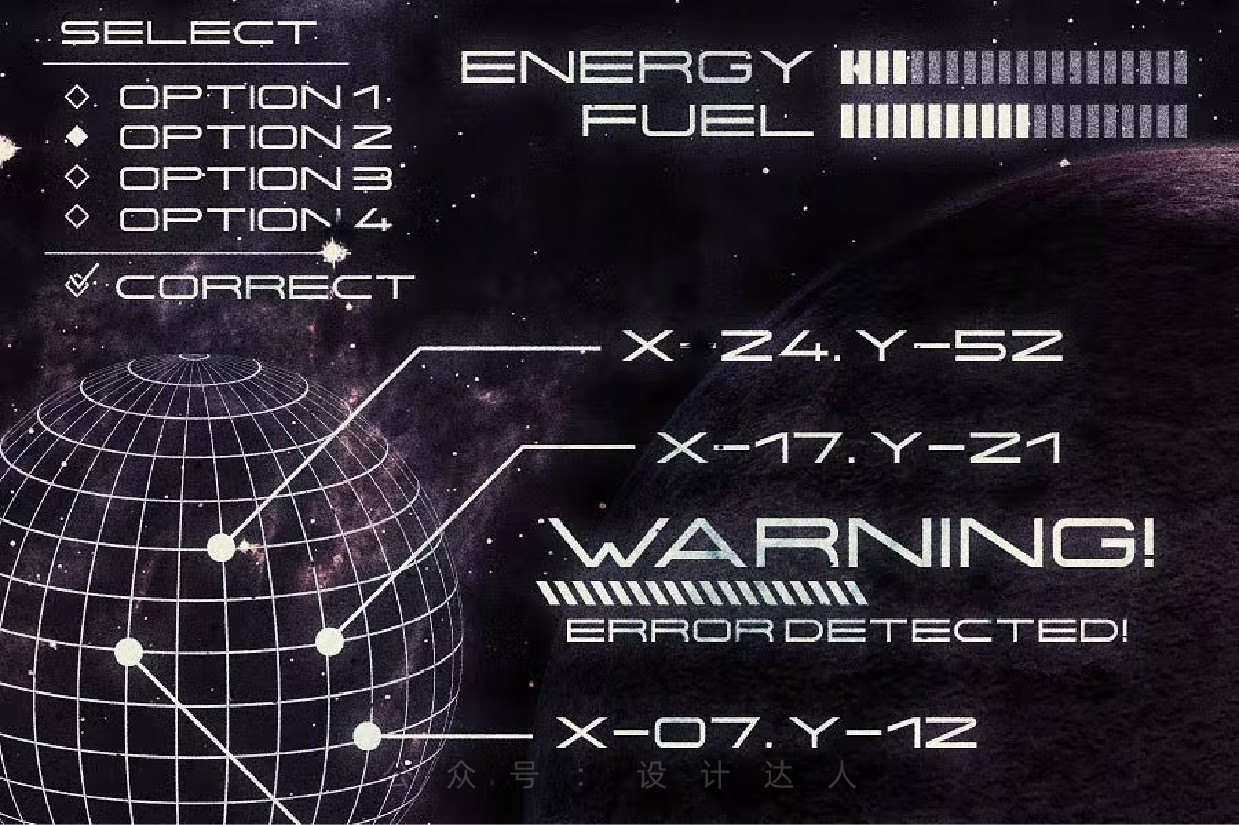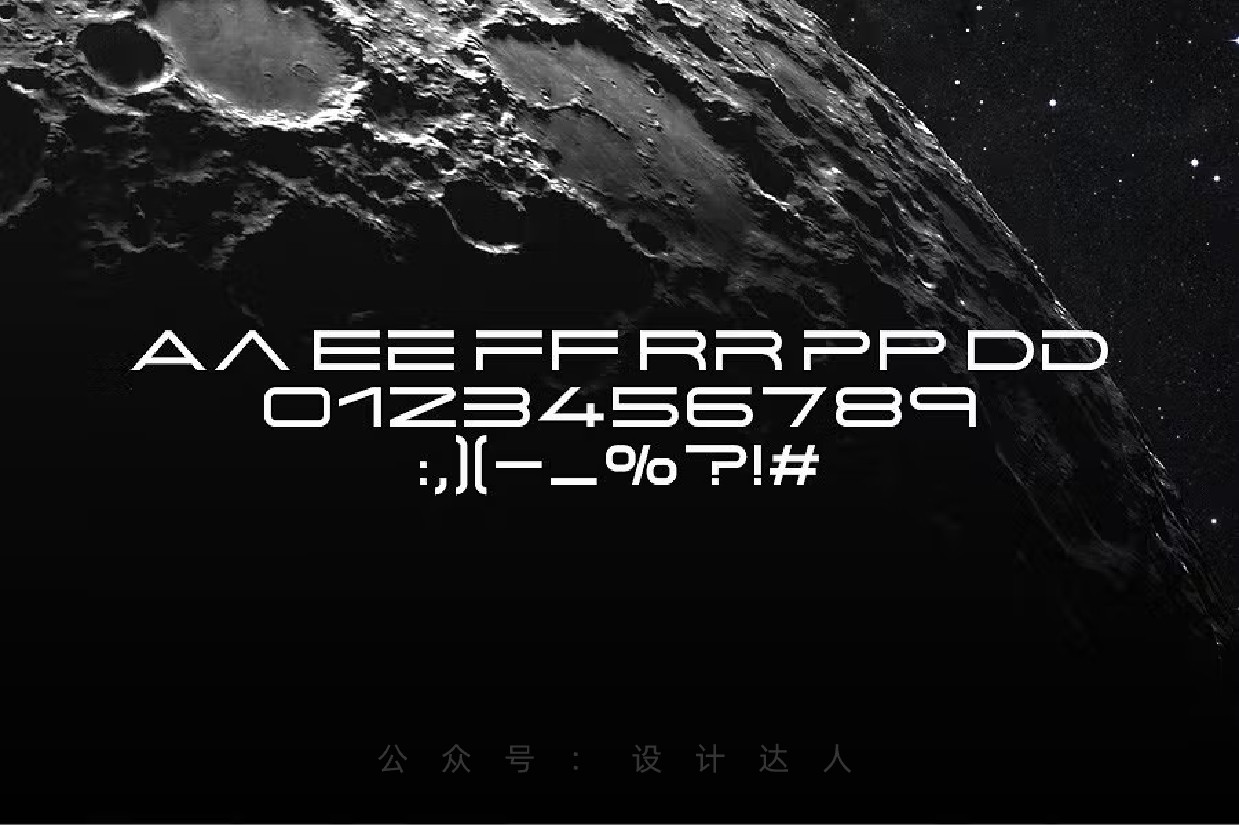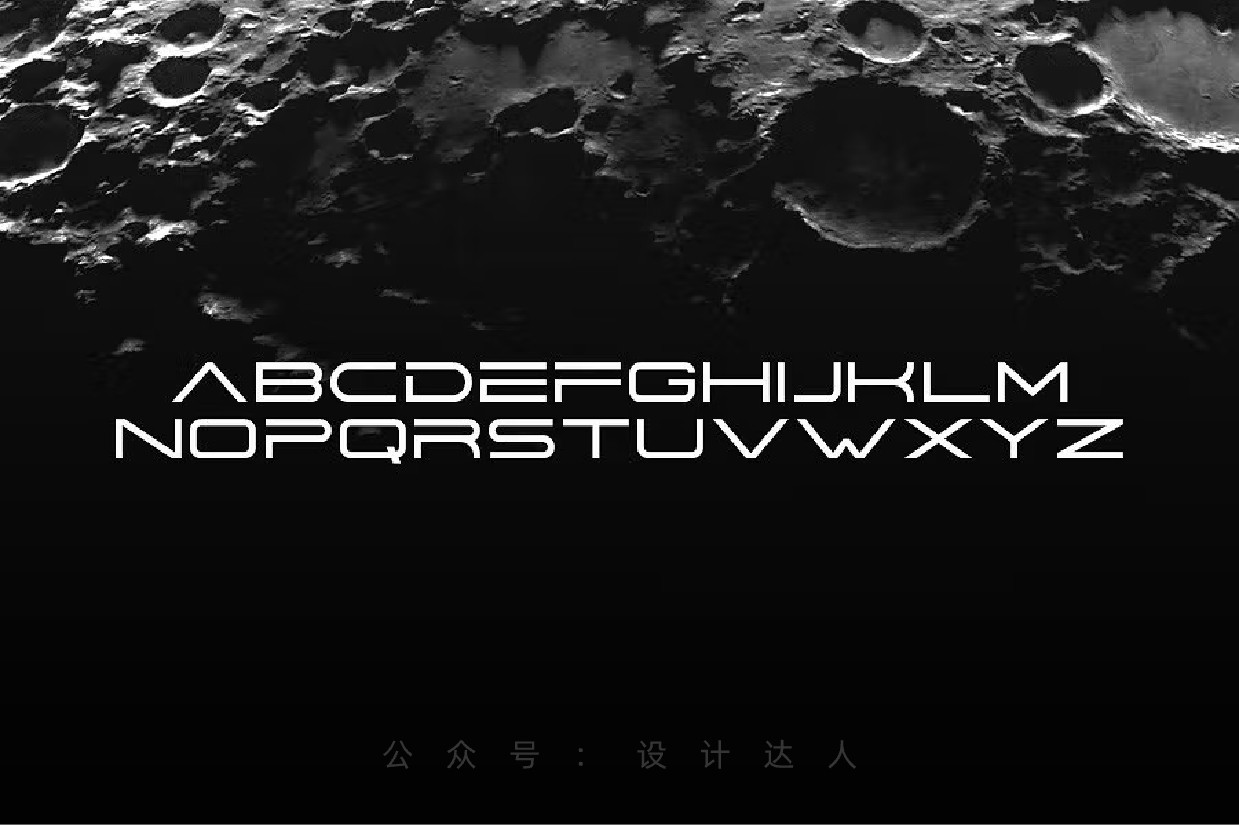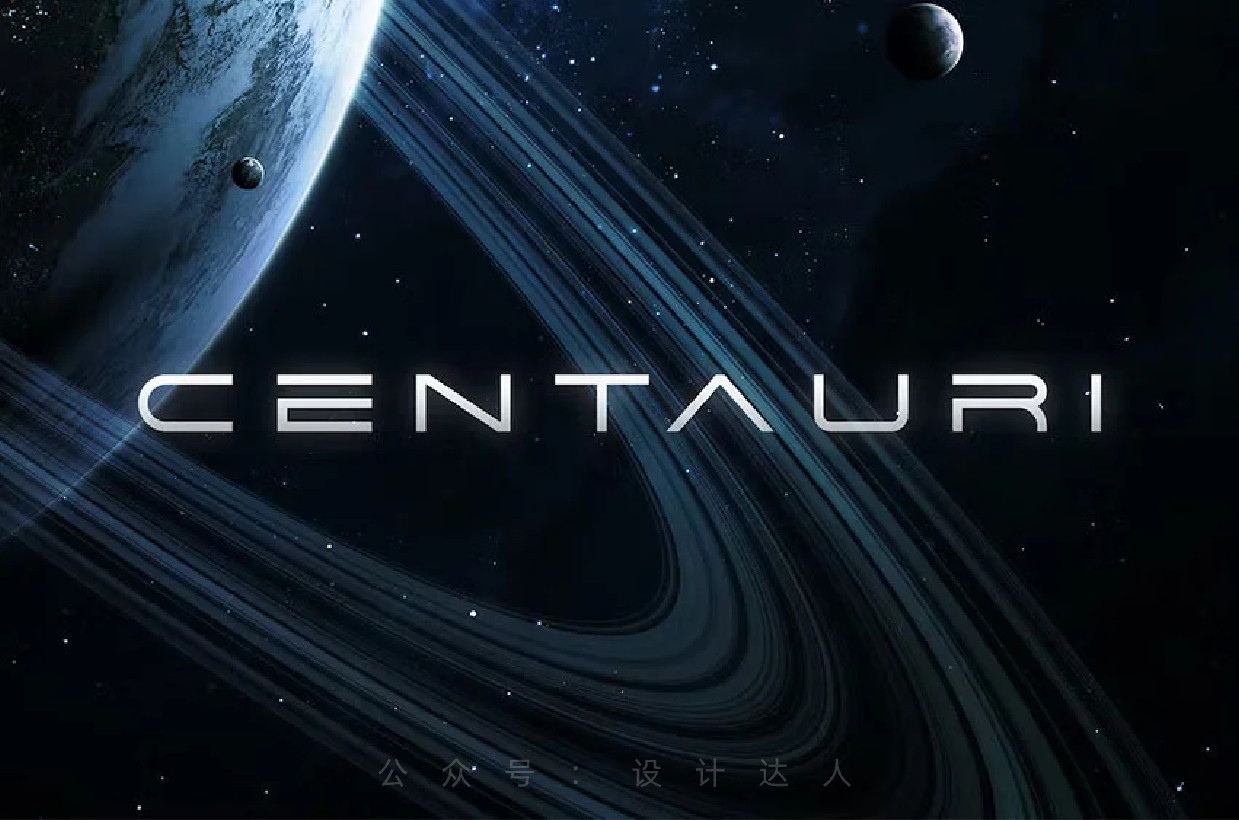
Centauri 科技未来极简主义字体(免费商用!附下载)
欢迎来到设计达人手工精选字体栏目,今天我要分享一个设计界的大新闻!你们知道吗?有一款字体,不仅拥有超现代的外观,而且还是免费商用的字体:Centauri。这个名字听起来就像是来自未来的呼唤。它的设计简洁而不失优雅,宽阔的字母间距仿佛在诉说着宇宙的无限可能,还免费商用!
字体特点:
- 包含所有大写英文字母,基础而全面。
- 提供多种替代字母,设计更灵活。
- 基本标点符号和数字一应俱全,满足你的各种设计需求。
- 字母间距宽阔,视觉效果震撼。
预览图:
为什么选择Centauri:
我们选择推荐Centauri,是因为它不仅能为你的设计带来未来感,还能让你的创意不受限制。它的免费商用特性,让每一个设计师都能无负担地使用,无论是个人项目还是商业大作,Centauri都能完美适应。